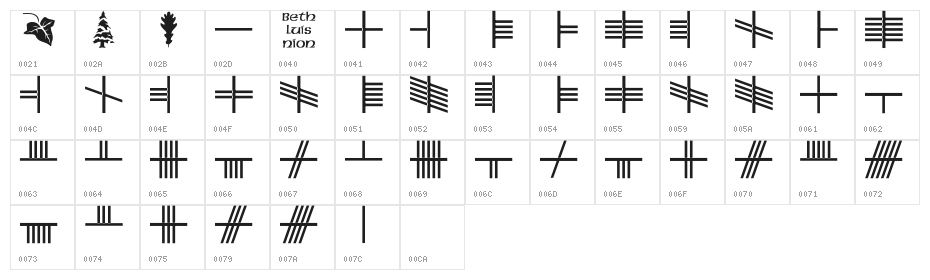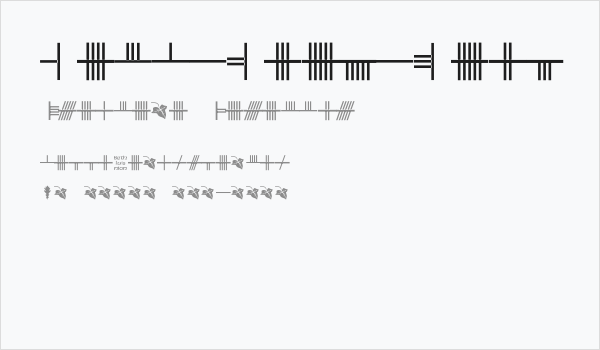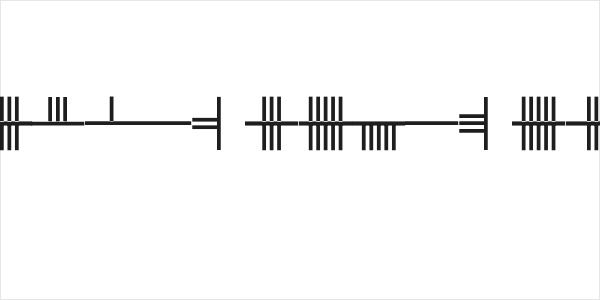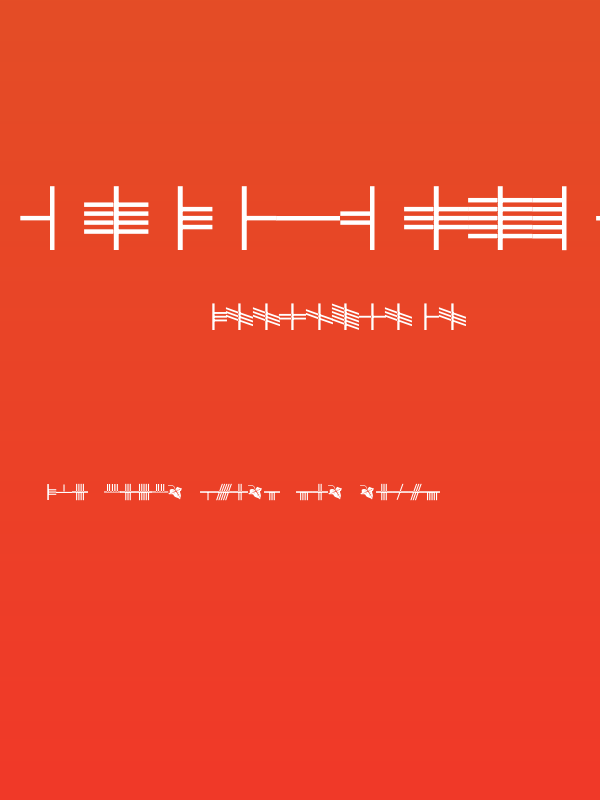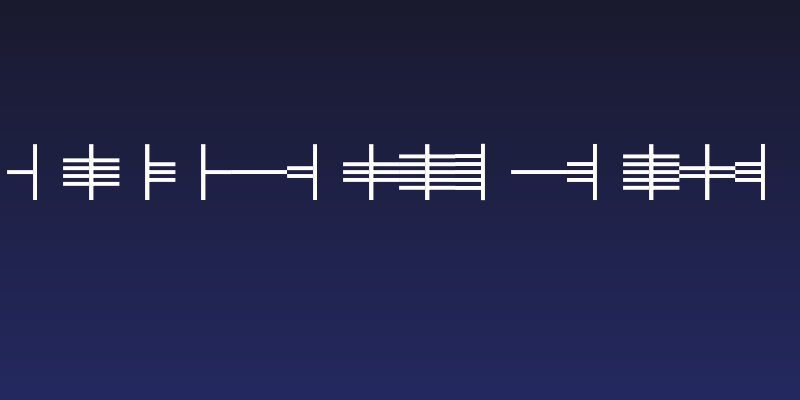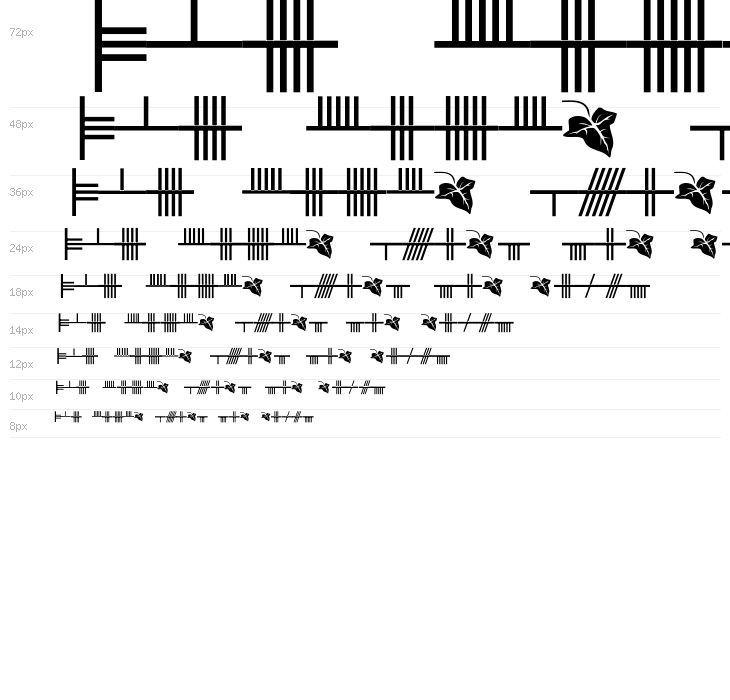
Beth-Luis-Nion Font
| Gesamtstil | Decorative, Organic, Nature-inspired |
| Anwendungsfall | Decorative elements, Borders, Patterns |
| Vorgeschlagene Projekte | Borders, dividers, nature-themed invitations, decorative patterns, scrapbooking, or ornamental accents. |